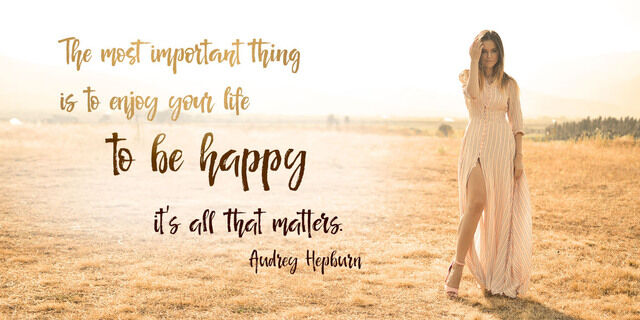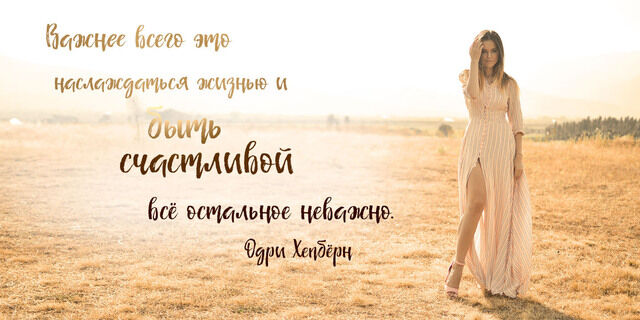
Senorita Cyrillic (1)
Рукописный текстурный шрифт Señorita (Сеньорита) был написан сухой кистью и отлично подойдет для дизайна брендов, плакатов, одежды, логотипов, заголовков сайтов, дизайна одежды, дизайна свадебных открыток и многого другого. Этот каллиграфический шрифт содержит полный набор прописных букв и 2 полных набора строчных букв и 43 лигатуры. Используйте чередующиеся строчные и двухбуквенные лигатуры, чтобы придать своим творениям идеальный вид ручного письма. Кириллическая часть шрифта содержит полный набор заглавных и строчных букв а также 17 лигатур, придающих реалистичный стиль вашей типографике. Многоязычная поддержка 32 языков на латинице и кириллице. Поддержка кириллицы в русском, белорусском, украинском, болгарском и казахском языках. Шрифт разработала Ирина Двилюк в 2021 году.